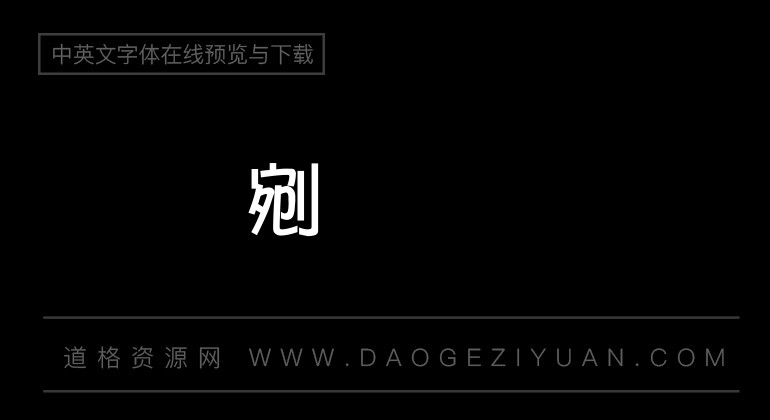
? 超研泽POP-2字体是一款大众化的中文字体,由超研泽设计团队设计,以简洁的外观和流畅的笔画为特点,适合用于报纸、杂志、商业广告、网页设计等多种场景。超研泽POP-2字体结合了中国传统字体的精髓,融入了现代设计的元素,为您的文字添加独特的视觉效果。文件名:ChaoYanZePOP-2TiFan-1.ttf
超研泽POP-2是一款非常不错的手写艺术字体,具有很好的视觉感,适合于文化类的宣传设计、商业类品牌的广告和产品包装设计以及个性化文字排版等较多场景。